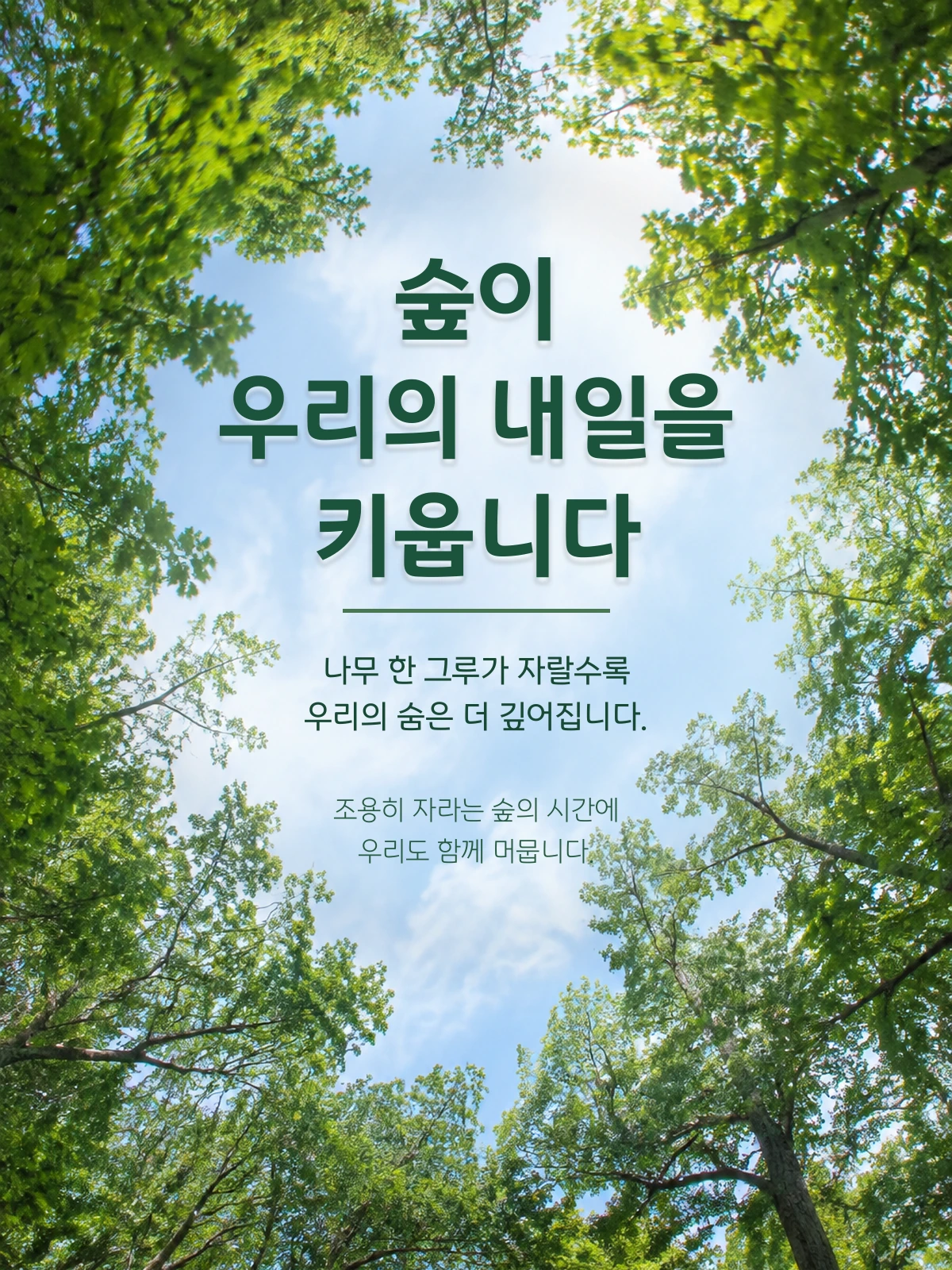
푸른숲체 무료폰트
푸른숲체 — 유한킴벌리에서 배포하는 무료 폰트입니다. 캠페인 로고와 따로 놀지 않도록 함께 그린, 숲의 온기를 곡선에 담아낸 본문용 고딕체
유한킴벌리가 2026년 6월에 공개한 서체로, 42년간 이어온 숲환경 공익 캠페인 우리강산 푸르게 푸르게의 철학을 담았습니다. 캠페인 브랜드를 새로 단장하면서 신규 로고와 캐릭터 우푸를 먼저 내놓았고 이 서체가 그 마지막 조각입니다.
로고와 서체가 따로 놀지 않도록 만든 점이 특징입니다. 제작사 설명에 따르면 신규 로고에 반영한 나뭇잎과 줄기 같은 조형 요소를 핵심 자음에 그대로 넣어, 로고와 서체가 하나의 브랜드 경험으로 이어지도록 했습니다. 전체 인상에 대해서는 곡선을 기반으로 한 고딕으로 친근하고 생기 있는 느낌을 살리면서 숲의 안정감과 유연한 에너지를 표현했다고 밝히고 있습니다.